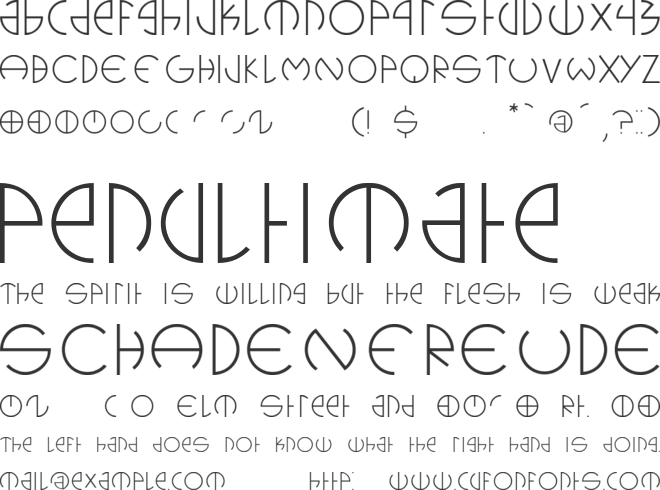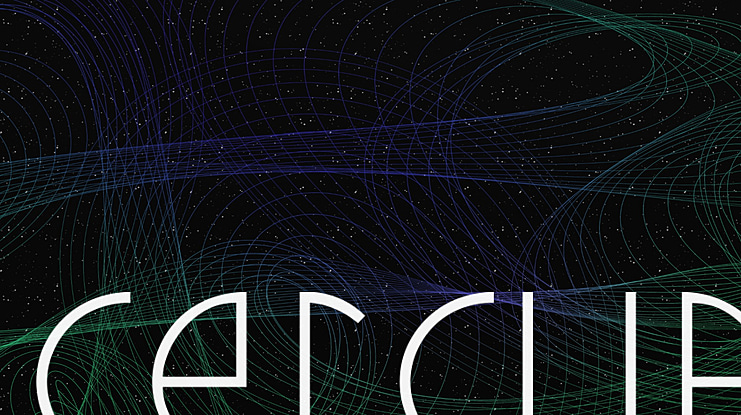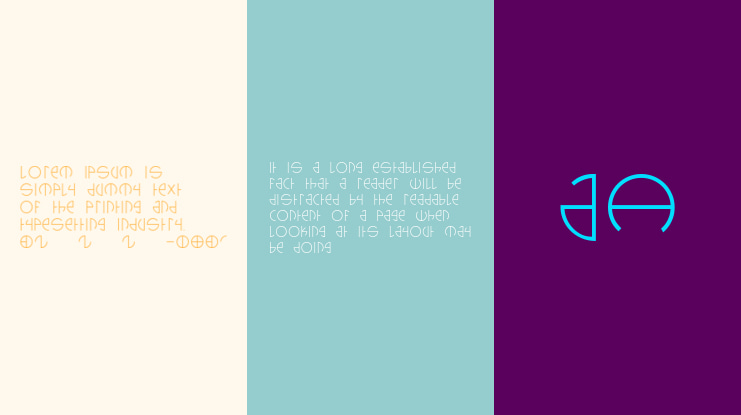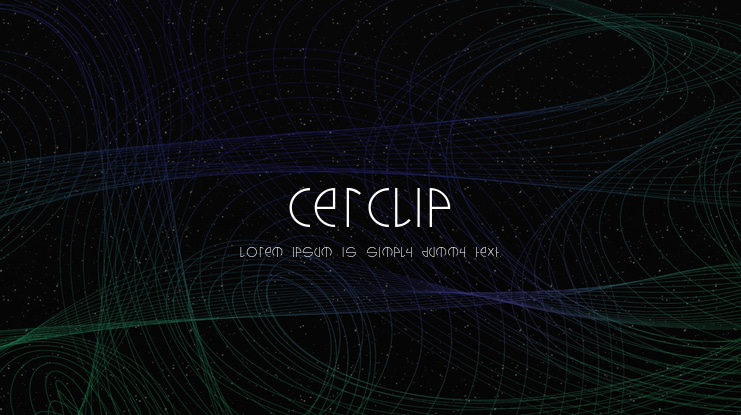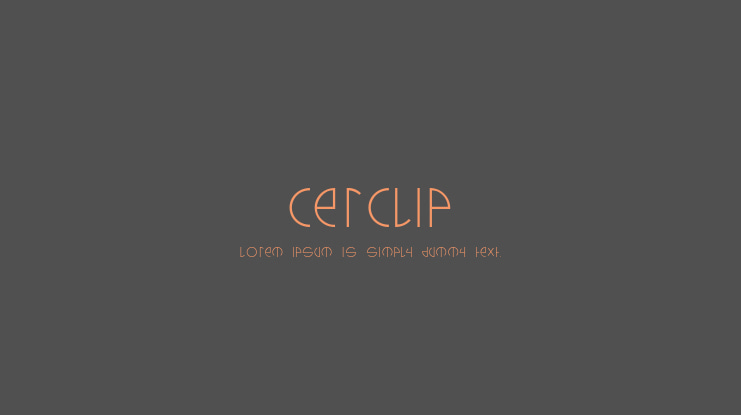
cerclip Font
Typographie construite sur la base du cercle. Chaque lettre suit le tracé du périmètre du cercle ainsi que deux diamètres (vertical et horizontal). La version bold de cette font est en cours.